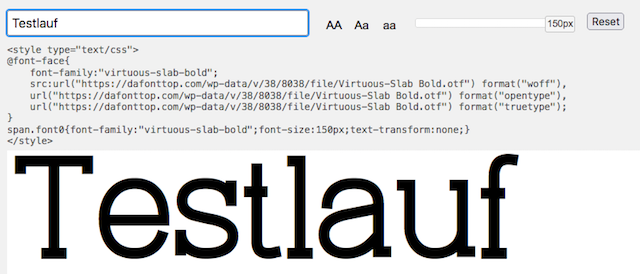
fontfamilie wird nicht vollständig angezeigt
ich möchte gerne die Font "Virtuous Slab Bold & Thin" für ein Logo verwenden. Ich habe diese über www.dafonttop.com runtergeladen und wie sonst auch die zip entpackt und aus der Familie nur Bold und Thin installiert. Ich nutze win10 und inscape! Als ich in inscape mir die Fonts nutzen wollte hat inscape nur thin erkannt. Beide sind aber installiert! Dies habe ich über Systemsteuerung "Schriftarten" geprüft! Habe es in einem word Dokument versucht, auch hier wird mir nur thin angezeigt.
Um der Vollständigkeitshalber habe ich versucht alle 6 Fonts in der Familie runterzuladen aber auch das ging nicht!
Das ist ein typischer Fehler in Freeware-Fonts von zweifelhafter Qualität. Die Schriftschnitte sind nicht korrekt stilverlinkt und stören sich deshalb gegenseitig in bestimmten Anwendungen. Wenn es unbedingt eine kostenlose Schrift sein muss, schau besser bei Google Fonts nach Alternativen. Da ist das Niveau etwas höher.
Die ist gar nicht schön zugerichtet … Ich kann dir nur raten, Ralfs Empehlung zu folgen. Bessere (kostenlose) Slabs findest du bei Google Fonts: https://fonts.google.com/?category=Serif,Display&query=slab und hier: https://www.fontsquirrel.com/fonts/list/classification/slab serif
Hallo @daniel1977, sofern die Fonts* korrekt installiert sind (also nicht TTF- und OTF-Dateien gemischt installiert wurden, beispielsweise), kannst du auch unter Windows auf alle Schnitte der Schriftart zugreifen. Du brauchst dafür möglicherweise aber ein (semi-)professionelles Desktop-Publishing-Programm. Mit den Programmen von Affinity (z. B. »Designer«) oder denen der Adobe Creative Suite (z. B. »InDesign«) sollte das gehen. Wenn du voraussichtlich nur den einen Logo-Job abschließen willst, kannst du dir dafür vielleicht die jeweiligen Testversionen herunterladen – das Zeitfenster dürfte reichen.
*übrigens Maskulinum – der Font
Bei der »Qualität« des Fonts ist nicht garantiert, dass er dort funktioniert. Such dir lieber einen möglichst ähnlichen Font (das wird nicht einfach, denn »virtuos slab« scheint auch gestalterisch ein paar Macken zu haben – ich hab mir den Font allerdings nicht heruntergeladen, sondern nur die Beispiele auf behance angeguckt und einen Test bei dafonttop gemacht). Sonst hilft vielleicht nur noch, dein Logo online zu samplen (z. B. so wie ich es bei dafonttop gemacht hab) und im Illustrator ö. ä. nachzuzeichnen und vor allem nachzubearbeiten.
Ob Du damit einen besseren rausfischst, ist ja auch noch nicht raus. Daher hier mal ein paar Empfehlungen kostenfreier Fonts mit den entsprechenden Strichstärken und ähnlicher Anmutung:
Wenn es etwas kosten darf, kommen wir natürlich optisch noch etwas näher ran, zum Beispiel hiermit:
Wir kennen jetzt die Komplexität dieses Logos nicht und dass Du CD-konform bleiben möchtest, ehrt Dich. Bei dieser schlechten Schriftqualität wärst Du aus meiner Sicht aber dann besser beraten, erstmal einen ästhetisch sauber gestalteten, technisch einwandfreien und für Lesetext funktionierenden Font zu haben und auf Basis dessen das Logo überarbeiten zu lassen.
Es gibt aber auch unzählige Erscheinungsbilder welche im Texteinsatz mit einem anderen Font arbeiten. Das heißt, es ist genauso gut denkbar eine Textschrift zu wählen die deutlich erkennbar anders aussieht. In Deinem Fall zum Beispiel eine ohne Slab-Serifen. Ein denkbares Paar wäre dann also die oben verlinkte Fakt Slab für Dein Logo und die Fakt für die Texte.
Nein. Was ich meinte, war folgendes: Versuch es ruhig mit einer Testversion. Testversionen sind über einen begrenzten Zeitraum gültig. Typisch sind hier 14 bis 30 Tage. Wenn du nur das eine Logo erstellen/bearbeiten willst, reicht dieser Zeitraum dafür bestimmt.
wenn es für Dein Logo eine Slab-Serif-Schrift sein soll (also eine Schrift mit ausgeprägten balkenartigen Füßchen), dann könnte diese Liste qualitativ guter kostenfreier Slab-Serif-Schriften für Dich eine Hilfe sein. Der Link führt Dich zu einer Liste, die hier im Forum zusammengestellt wurde, was für einen wirklich brauchbaren Qualitätsstandard der darin aufgeführten Schriften spricht. :-D